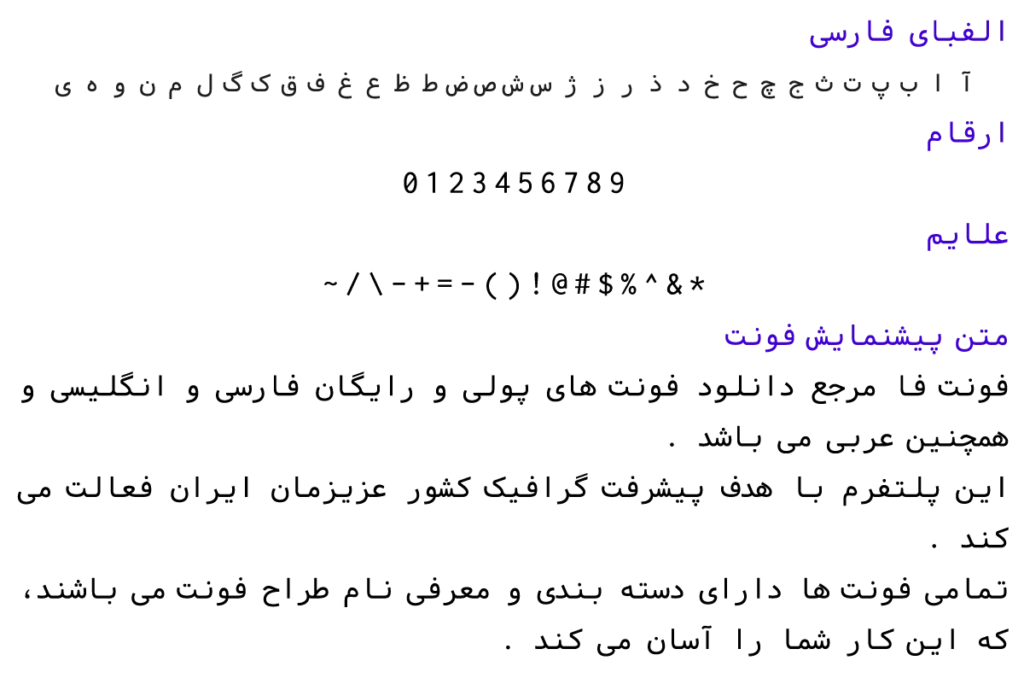
پیشنمایش فونت وزیرکد
فونت فارسی وزیرکد - Vazir Code
توضیحات و معرفی فونت وزیرکد
فونت فارسی وزیرکد ( Vazir Code ) از مجموعه فونت های آزاد می باشد، همچنین نوع فونت طراحی وب می باشد.
فونت فوق العاده زیبای معرفی شده توسط صابر راستی کردار در سال 1395 طراحی و ساخته شده است.
فونت وزیر کد از نوع monospaced برای کدنویسی ترکیب شده با فونت Inconsolata و Hack می باشد.
همچنین این فونت بر مبنای فونت وزیر متن باز طراحی شده است.
همچنین فونت وزیرکد در 4 وزن ساخته شده است.
در لیست زیر می توانید وزن این فونت فوق العاده زیبا را ببینید.
• Vazir Code Regular
• Vazir Code Extra Height
• Vazir Code Hack
• Vazir Code Hack Extra Height
مقایسه دو نسخه Inconsolata و Hack
در عکس زیر نسخه فونت Inconsolata را می توانید مشاهده کنید
Inconsolata
همچنین در تصویر زیر نسخه فونت هک Hack را می توانید مشاهده کنید
Hack
نقل قول از طراح این فونت
نسخه‌های با ارتفاع بیشتر (جهت حل مشکل نمایش در برخی برنامه‌ها) با عنوان Extra-Height در بسته فونت موجود می‌باشد.
نکته: توجه داشته باشید که در هنگام استفاده از نیم‌فاصله یا علائمی همچون اِعراب، عرضی برای آن در نظر گرفته نمی‌شود.